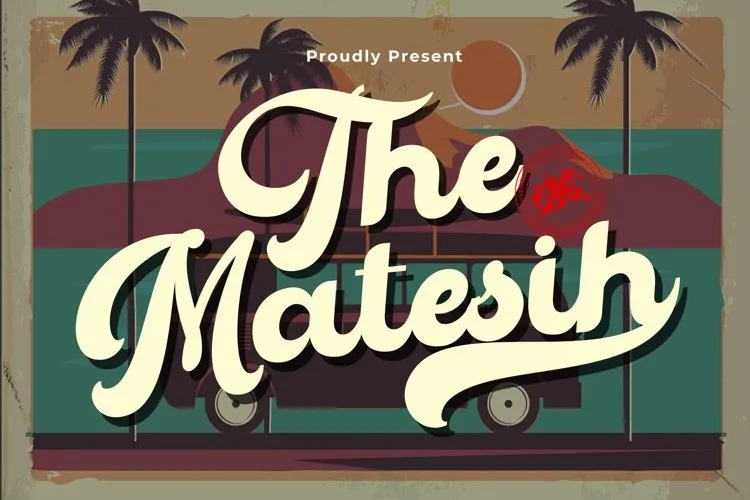
The Matesih Font – Download Grátis
A “The Matesih Font” é uma elegante fuente script desenvolvida pelo designer independente FallenGraphic Std, com base na arte naturalmente escrita por mãos humanas. Esta fuente é perfeitamente adequada para qualquer projeto de design, seja branding, citações ou qualquer outra aplicação. Ela enriquece seu trabalho de design e dá um toque poderoso a ele. Seu estilo fluido e suave combina perfeitamente com diferentes estilos de design, tornando-o uma opção versátil para quem está em busca de uma fuente que realçará o profissionalismo e a criatividade de suas criações. O “The Matesih Font” é um excelente complemento para qualquer projeto que valorize estilo e elegância.